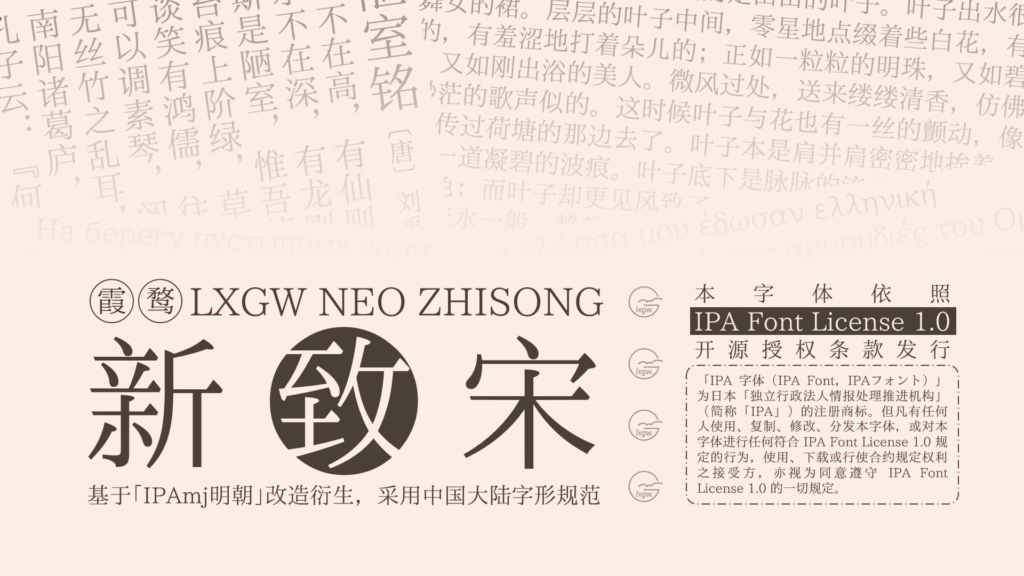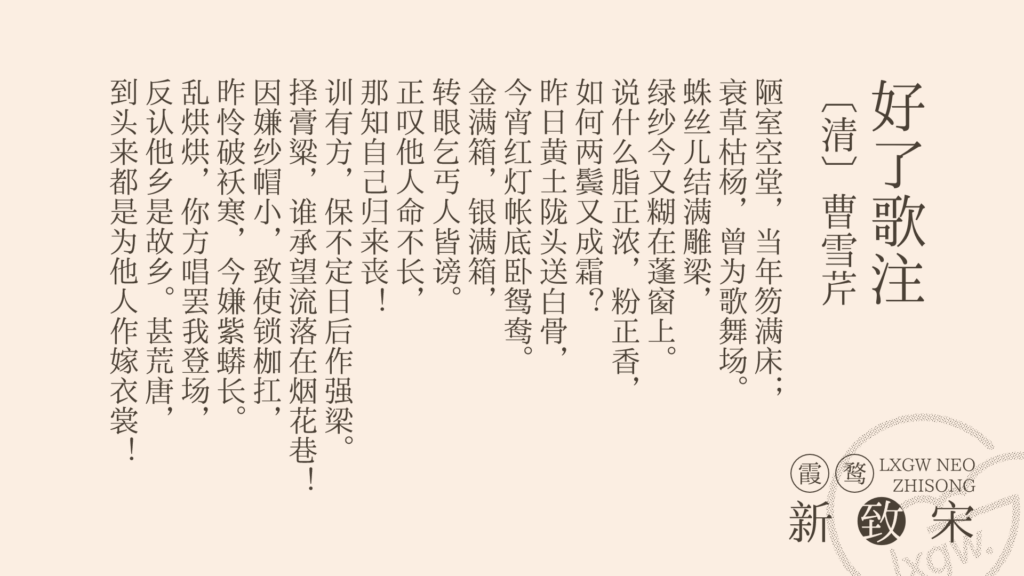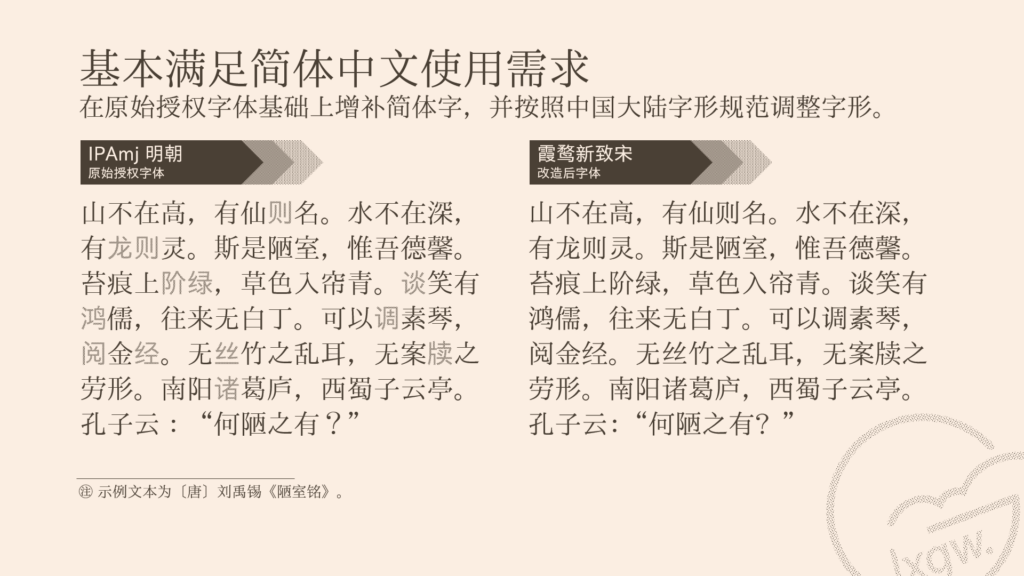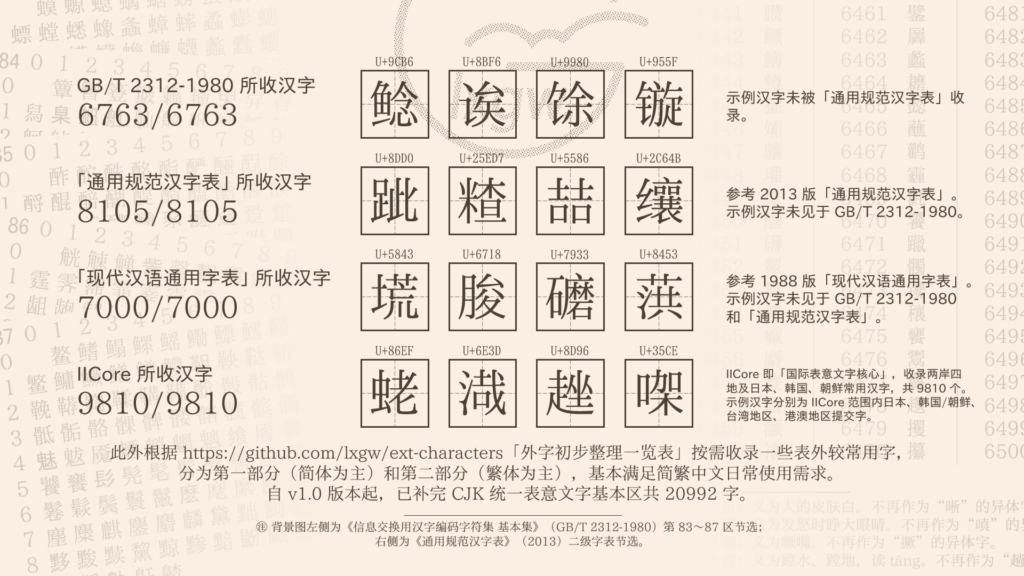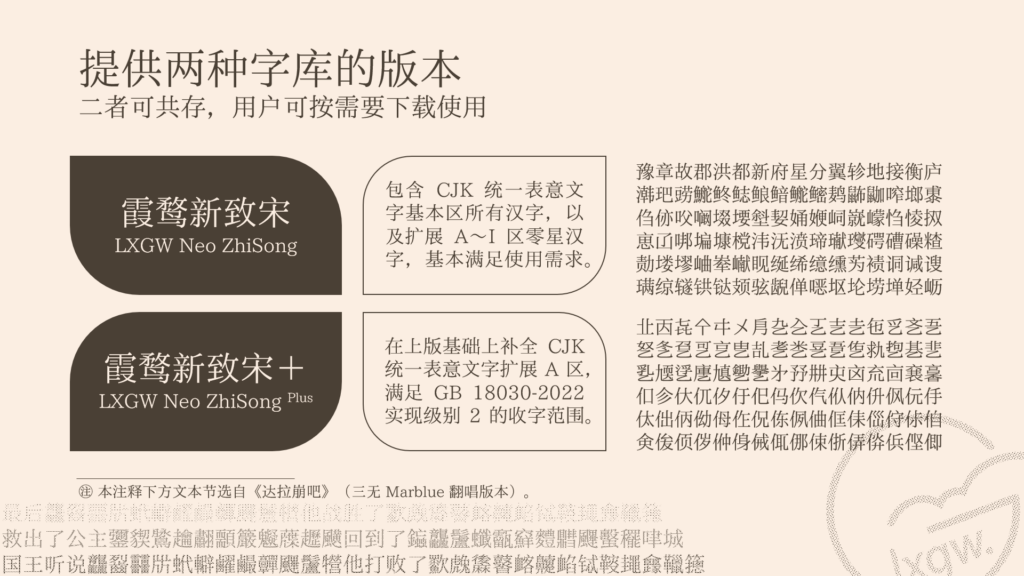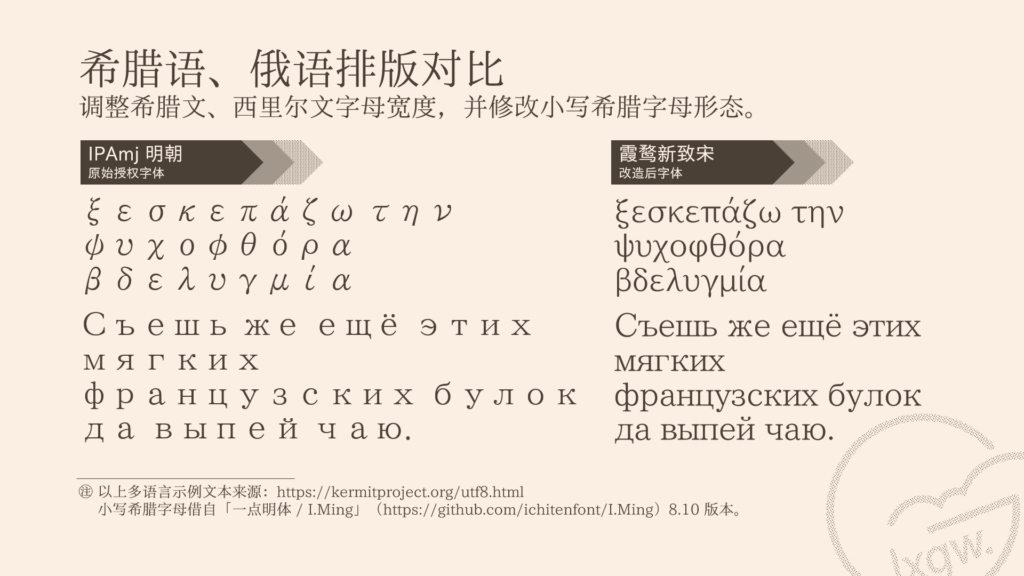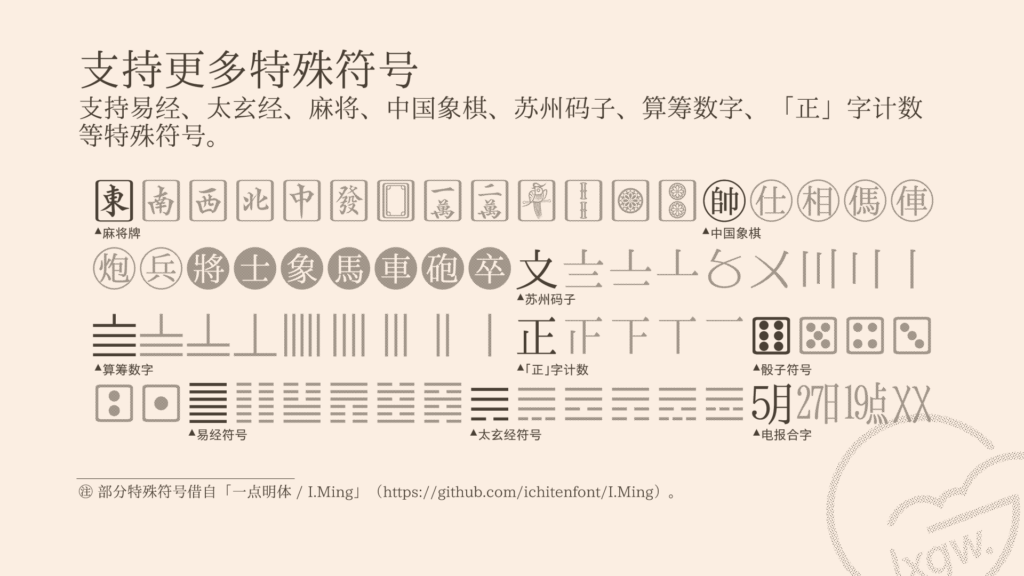
这是一款基于「IPAex明朝」「IPAmj明朝」的中文开源字体,是将日本写法的字体改造成中国大陆规范写法的尝试。
本字体是「霞鹜新晰黑」的姊妹字体,尝试在「IPAmj明朝」原有字形的基础上,将其改造成中国大陆规范字形。除此之外,重做了希腊字母和西里尔字母,与原字体拉丁字母部分风格基本一致,更适合现代希腊文及西里尔文的排版;新增对越南语拉丁字的显示支持。符号方面,支持易经八卦和六十四卦符号、太玄经八十一首符号、麻将符号、中国象棋符号、算筹数字、「正」字计数等特殊符号。